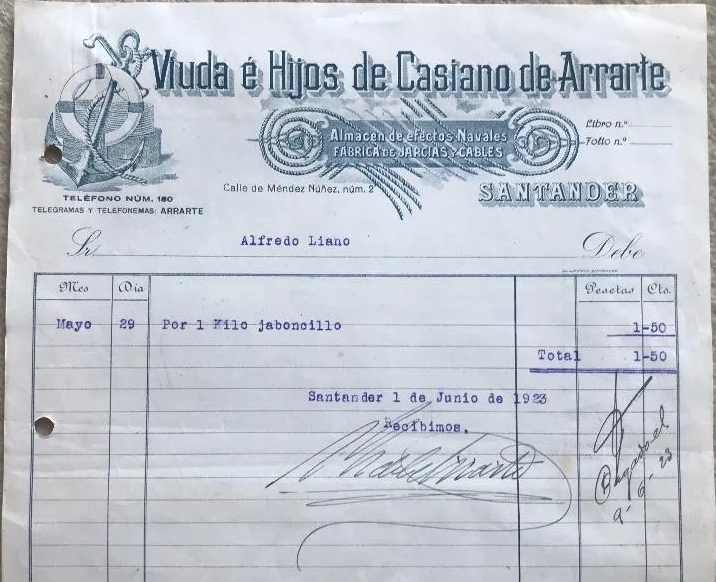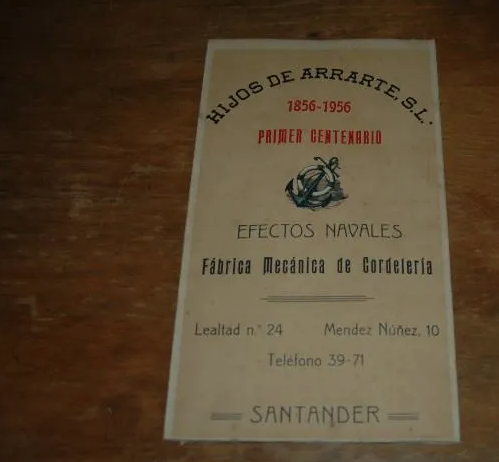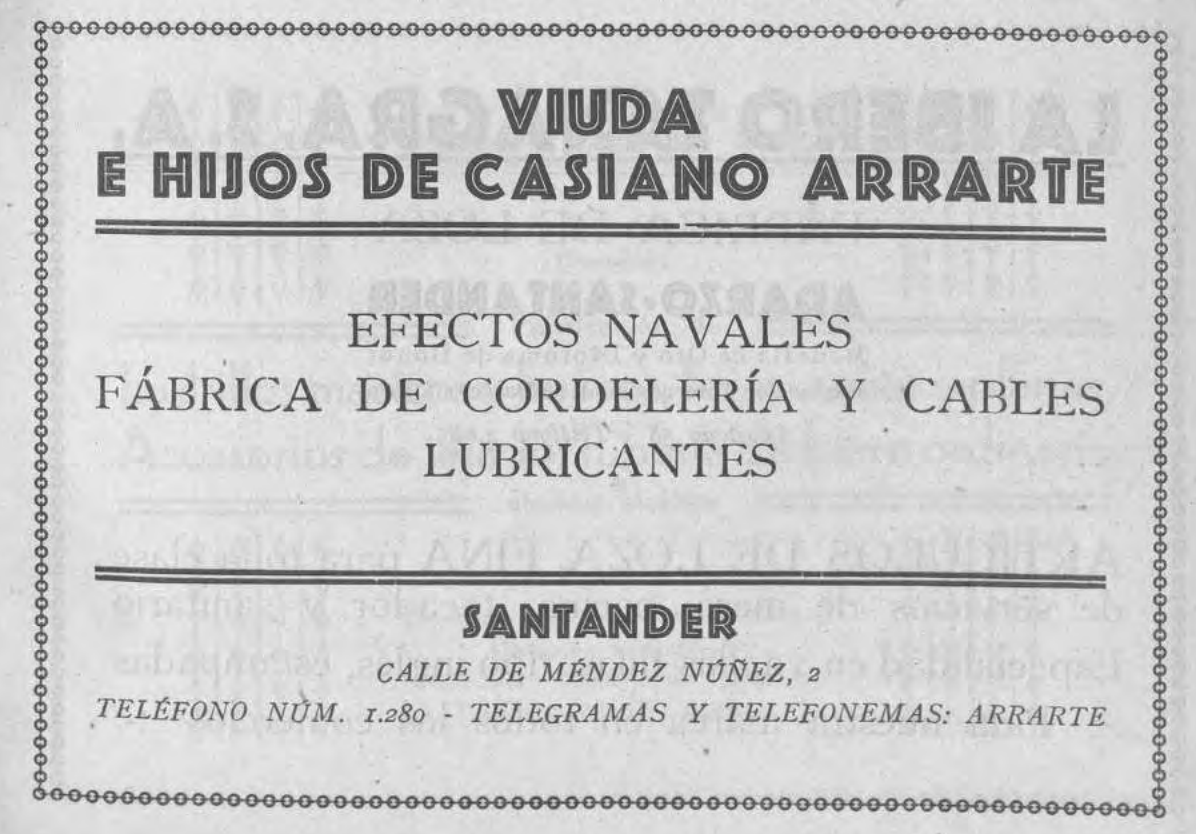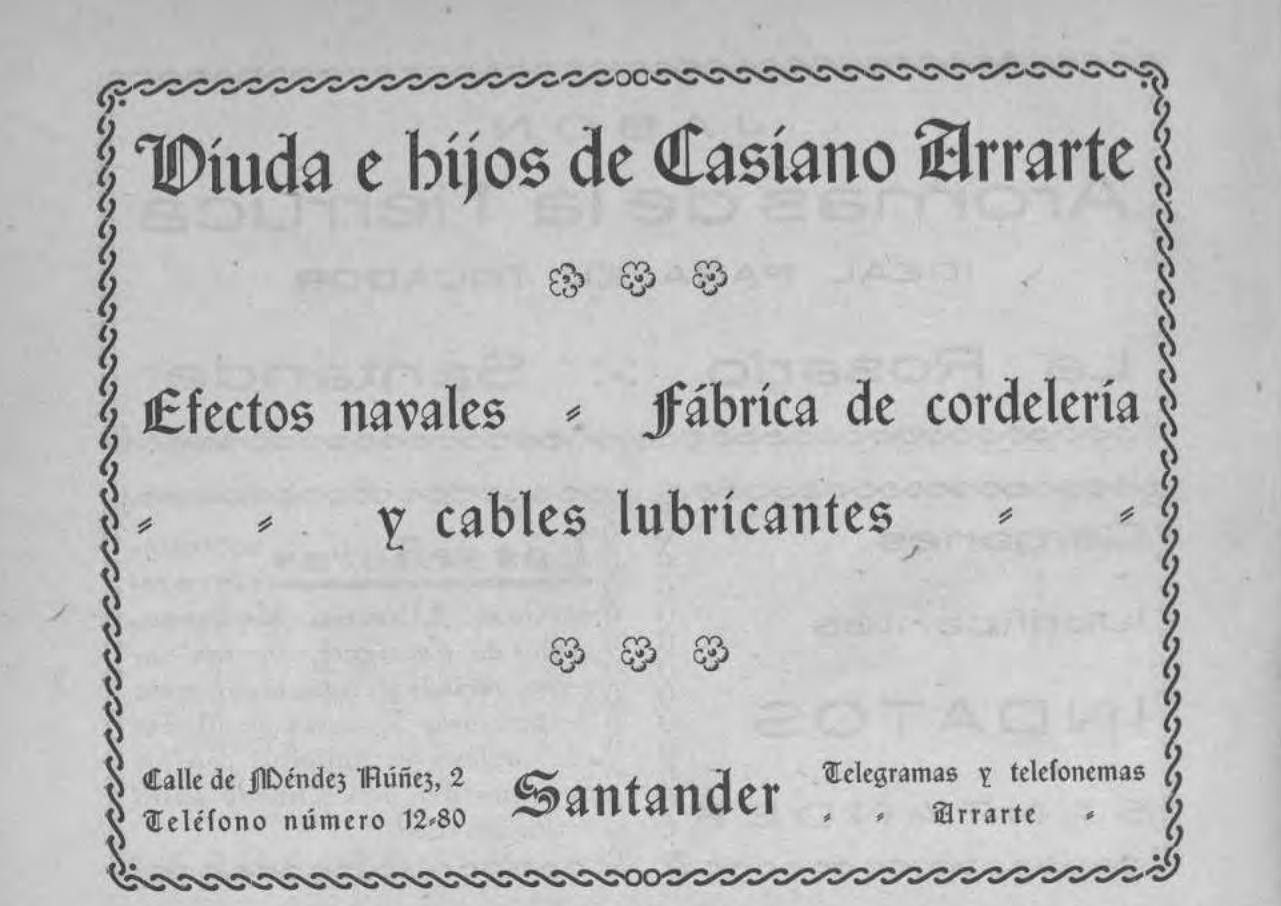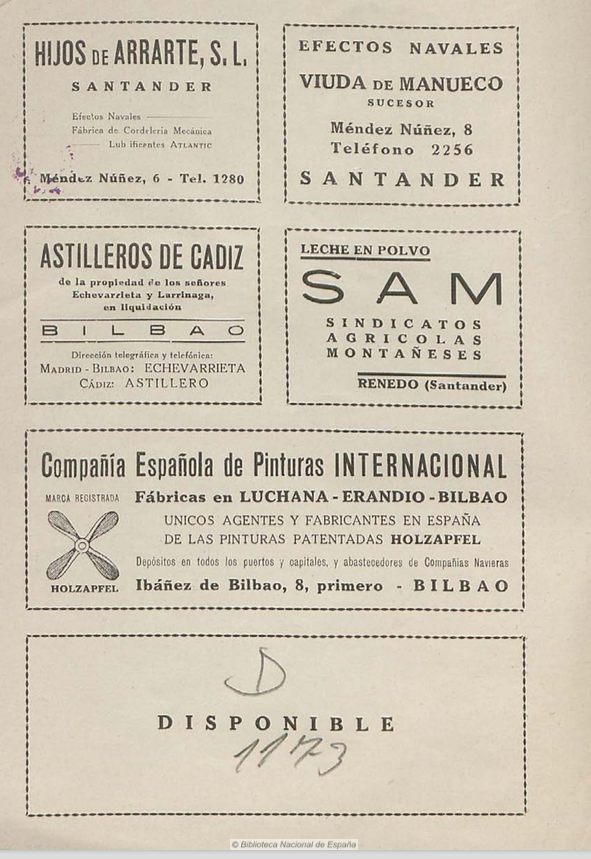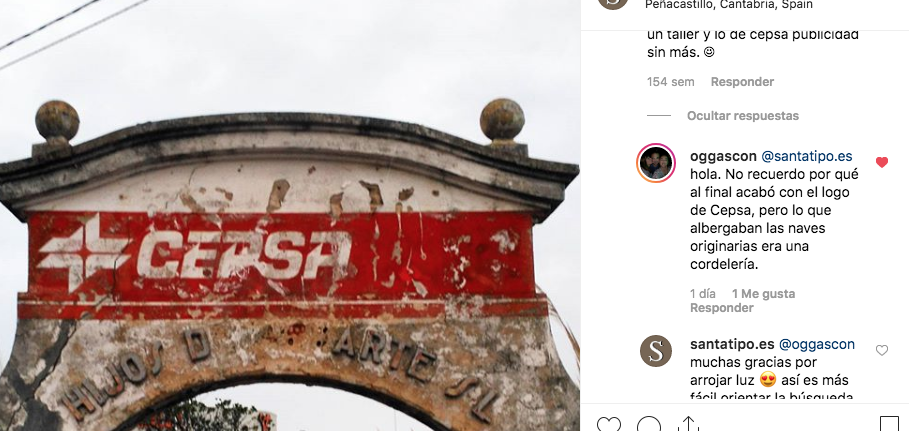
Descubrir un pedacito de historia gracias a las RRSS: El tinglado de Peñacastillo
Una de las patas del proyecto es la gente, ya sea o bien preguntando en persona a pie de comercio o través de las Redes, donde parte de nuestra memoria colectiva sirve para poder construir trozos de microhistorias y rescatar parte de ella abriendo una linea de investigación. Este es un caso claro.
En 2016 publicaba en instagram esta foto:
Se trata de un arco y dintel, que queda en pie en una parcela en el Primero de Mayo, cerca del gimnasio y junto a las naves industriales. En el destaca la siguiente inscripción (aparte del logo de Cepsa)
HIJOS D[…] […]ARTE SL
La foto ha estado ahí colgada hasta que el pasado día 25 de mayo de 2019 un usuario dio una pista muy interesante:
CORDELERIA. Esa palabra ha sido clave para al menos orientar la búsqueda y obtener la siguiente hipótesis de lo que se trataba:
Las cordelerías son industrias manufactureras especializadas en la creación de cuerdas, jarcias y cabos para uso marítimo. En Santander comienzan a ser habituales a partir del S.XVIII cuando hay una alta actividad portuaria. Para ello uno de los primeros tinglados que se construye es el de Becedo y ocuparía lo que hoy desde la entrada del Pasaje de Peña hasta la Plaza de Juan Carlos I. En el XIX y comienzos del XX es una actividad comercial vinculada a la ciudad. Con esos datos, ya se puede filtrar una primera búsqueda. Y comienzan a dar los primeros resultados. La primera referencia nos la da Simón Cabarga, que habla de que a finales del XIX sobre el entorno de la Calle Cádiz:
Al llegar a Navas de Tolosa, salvaba una solución de continuidad impuesta por la entrada a la Rampa de Sotileza y después no era ya mas que camino rural prolongado por encima del muro del patio de llegada a la estación del Norte y junto a los talleres de Corcho hasta perderse por un caminejo sombreado por los eucaliptos al pie de la Peña del Cuervo. Este caminejo podía muy bien haberse llamado «paseo de los melancólicos» y en él retorcían el cáñamo los operarios de la cordelería de Arrarte que, los días de lluvia, hacían sus labores dentro de unos muy largos tendejones.
Simón Cabarga, «Santander en la Historia de sus calles» p.53. Instituto Cultural de Cantabria (1980)
Segundo dato interesante: Cordelería de Arrarte. Ahora podemos reconstruir las letras del Dintel y la hipótesis de su trayectoria tras una serie de búsquedas con esos datos.
HIJOS D(E) (ARR)ARTE SL
La empresa la fundó Casiano Arrarte en 1856. Tras su fallecimiento tanto viuda como hijos continuaron con el negocio en Méndez Nuñez, 2. Esto aparece documentado como una factura de 1923 en una web de coleccionismo:
y en anuncios de la Revista de Santander  (1930 – 1933)
Probablemente en 1936, todo hace indicar que, cambiaron su denominación social por el actual «Hijos de Arrarte, SL.», como así se puede atestiguar por un anuncio de la Revista de la Marina Civil de 1936 digitalizada en la BNE.
En 1956 celebran en centenario de la empresa, de ahí que ubicar su fundación sea gracias a este folleto publicitario, y se puede interpretar que es están en un momento de crecimiento, porque ya hay otra oficina en Lealtad.
¿Cuándo se ubican en la zona de Peñacastillo? ¿cuándo entra Cepsa? ¿cuándo cesa el negocio? a esta última pregunta cabe responder que aparecen con una nueva ubicación, y cambio social, en la zona de San Martín del Pino (cerca de Carrefour) y con actividad a finales de los 90s y comienzos de 2000. Por lo tanto estamos hablando de una Empresa familiar, histórica y centenaria que hubo en Santander, y de la cual sólo nos queda un fragmento en un dintel y elementos gráficos que se subastan.
Este ha sido un ejercicio práctico para demostrar, que a veces las letras nos cuentan cosas que tirando de los hilos adecuados, y nos permite  ir construyendo parte de nuestra historia comercial y de las calles. Por esto mismo hay considerar los rótulos como un Patrimonio Gráfico y Visual, porque nos hablan de épocas, historias locales y memoria colectiva.